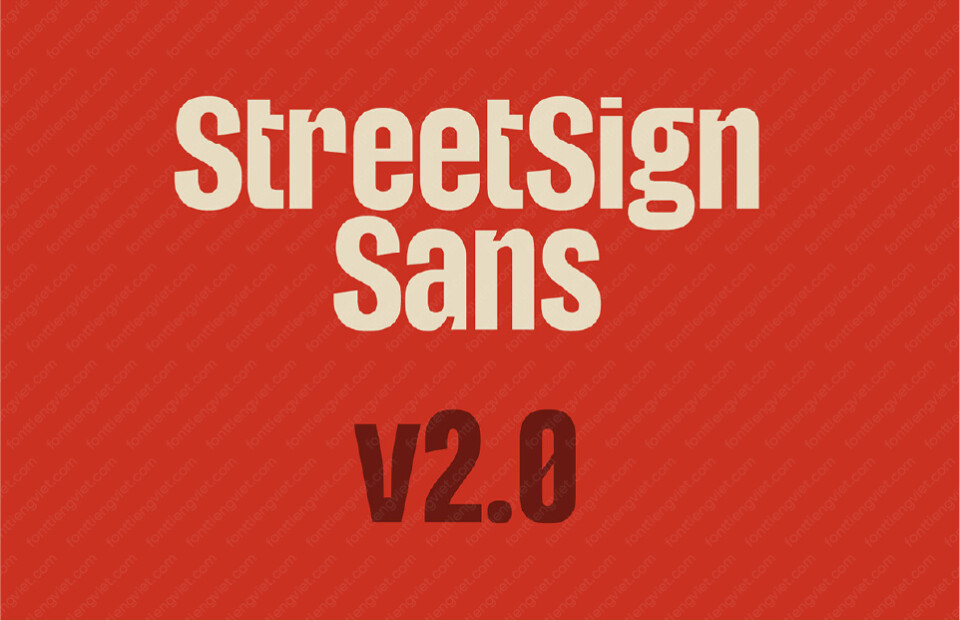
Font Tiếng Việt BD StreetSign Sans (StreetSign Sans 2.0 )
Trong thế giới đồ họa hiện đại, việc lựa chọn một bộ Font Miễn Phí chất lượng luôn là ưu tiên hàng đầu của các nhà thiết kế. Một trong những cái tên đang gây chú ý chính là Font Tiếng Việt BD StreetSign Sans (StreetSign Sans 2.0 ). Đây là phiên bản nâng cấp hoàn hảo, mang đến sự kết hợp tinh tế giữa phong cách cổ điển của các biển báo đường phố và hơi thở hiện đại của nghệ thuật typography. Với bộ gõ tiếng Việt đầy đủ, phông chữ này giúp bạn truyền tải thông điệp một cách rõ ràng và mạnh mẽ hơn bao nhiêu hết.
Khám phá đặc điểm của Font Tiếng Việt BD StreetSign Sans (StreetSign Sans 2.0 )
Bộ font này được thiết kế với các đường nét dứt khoát, độ dày vừa phải, tạo cảm giác tin cậy và chuyên nghiệp. Phiên bản 2.0 đã khắc phục hoàn toàn các lỗi hiển thị dấu tiếng Việt, giúp các bạn học sinh và giáo viên dễ dàng ứng dụng vào bài giảng hoặc báo cáo sáng tạo.
Tính ứng dụng đa dạng trong giáo dục và đời sống
Nhờ cấu trúc chữ không chân (sans-serif) dễ đọc, Font Tiếng Việt BD StreetSign Sans (StreetSign Sans 2.0 ) cực kỳ phù hợp cho các tiêu đề lớn, banner sự kiện trường học hoặc các thiết kế poster tuyên truyền. Khả năng hiển thị tốt trên cả màn hình kỹ thuật số và bản in giúp sản phẩm của bạn luôn chuyên nghiệp trong mọi hoàn cảnh.
Cách sử dụng Font Tiếng Việt BD StreetSign Sans (StreetSign Sans 2.0 ) hiệu quả
Để phát huy tối đa vẻ đẹp của phông chữ này, bạn nên kết hợp nó với các màu sắc tương phản mạnh như trắng trên nền xanh navy hoặc vàng trên nền đen. Điều này giúp tái hiện lại phong cách biển báo đường phố đặc trưng mà bộ font hướng tới.